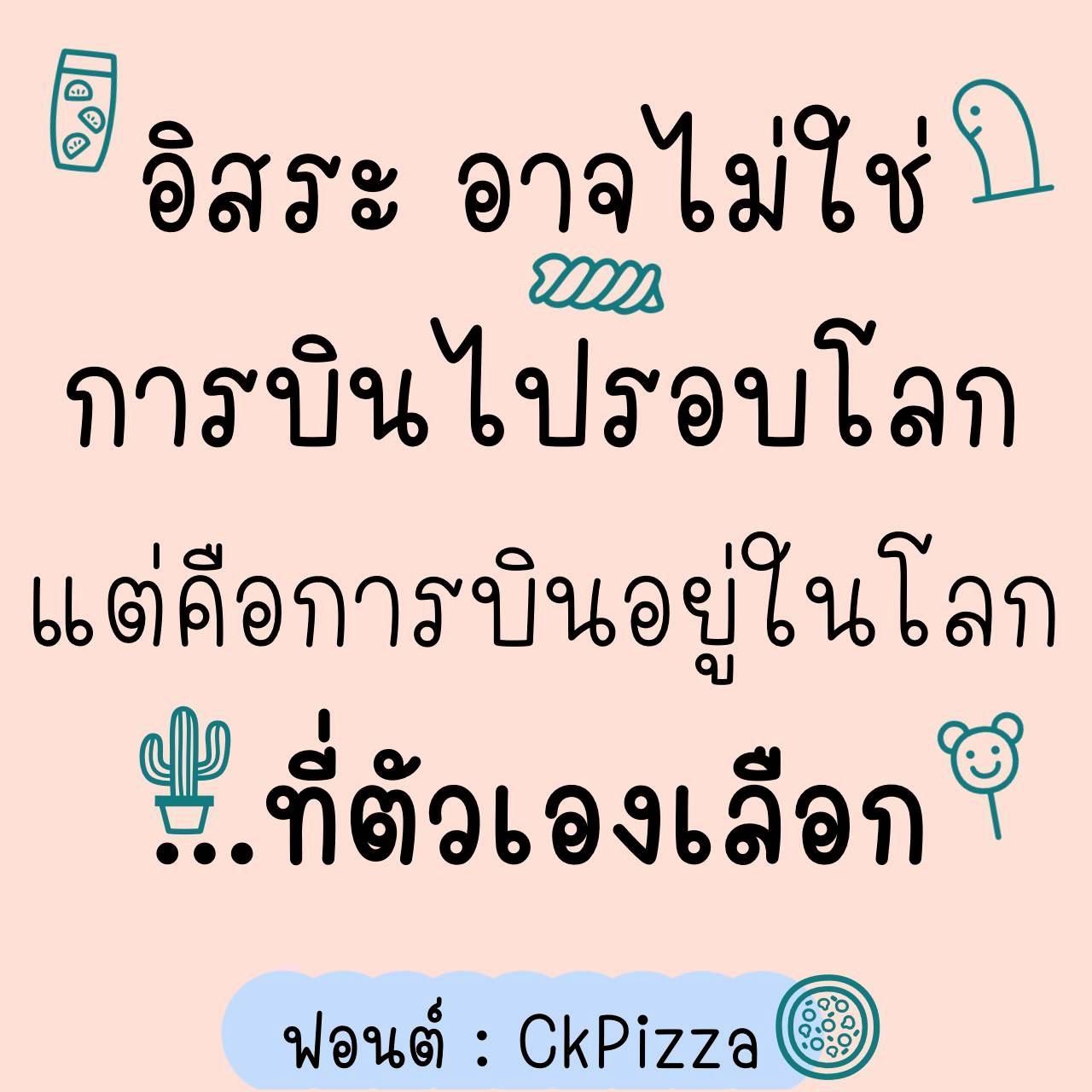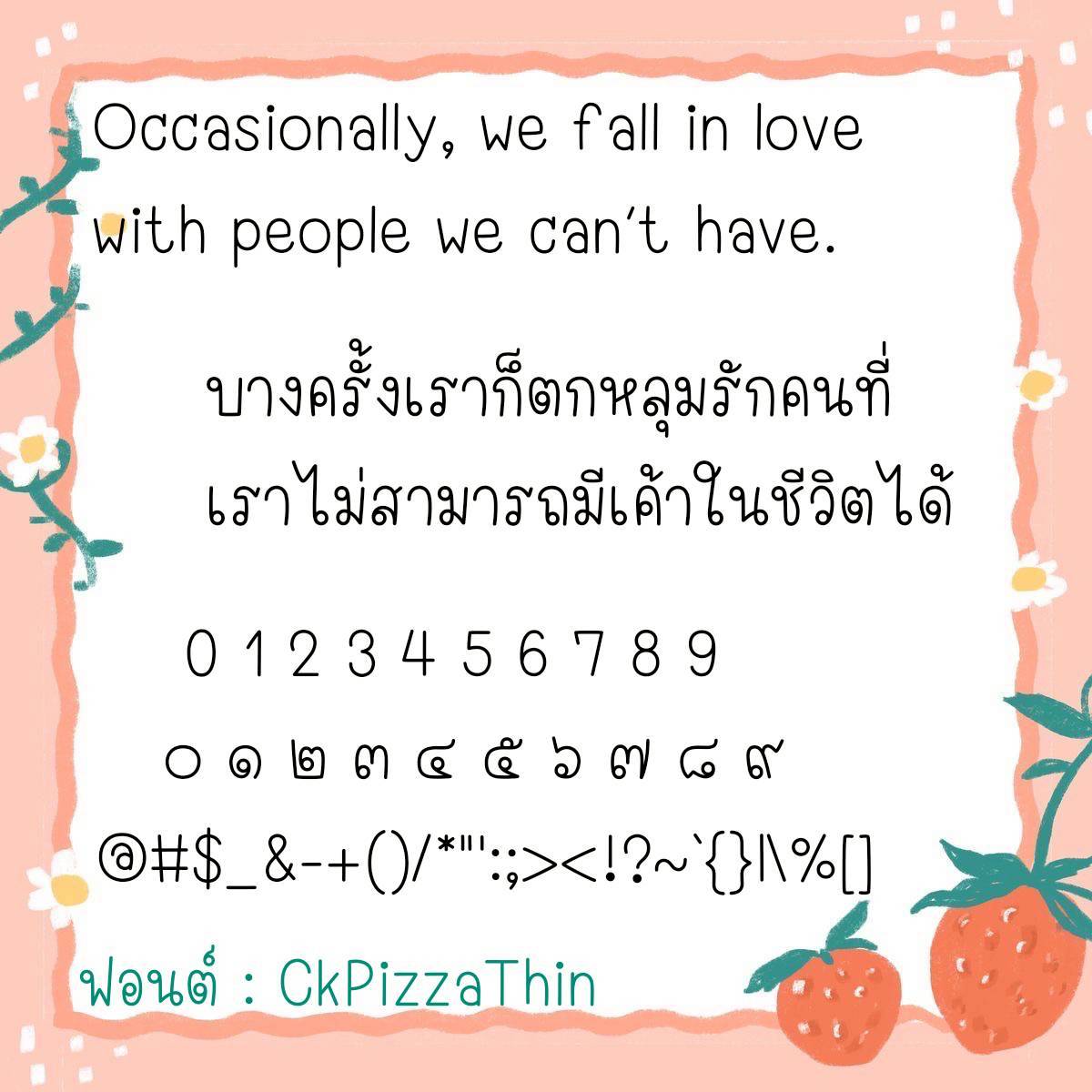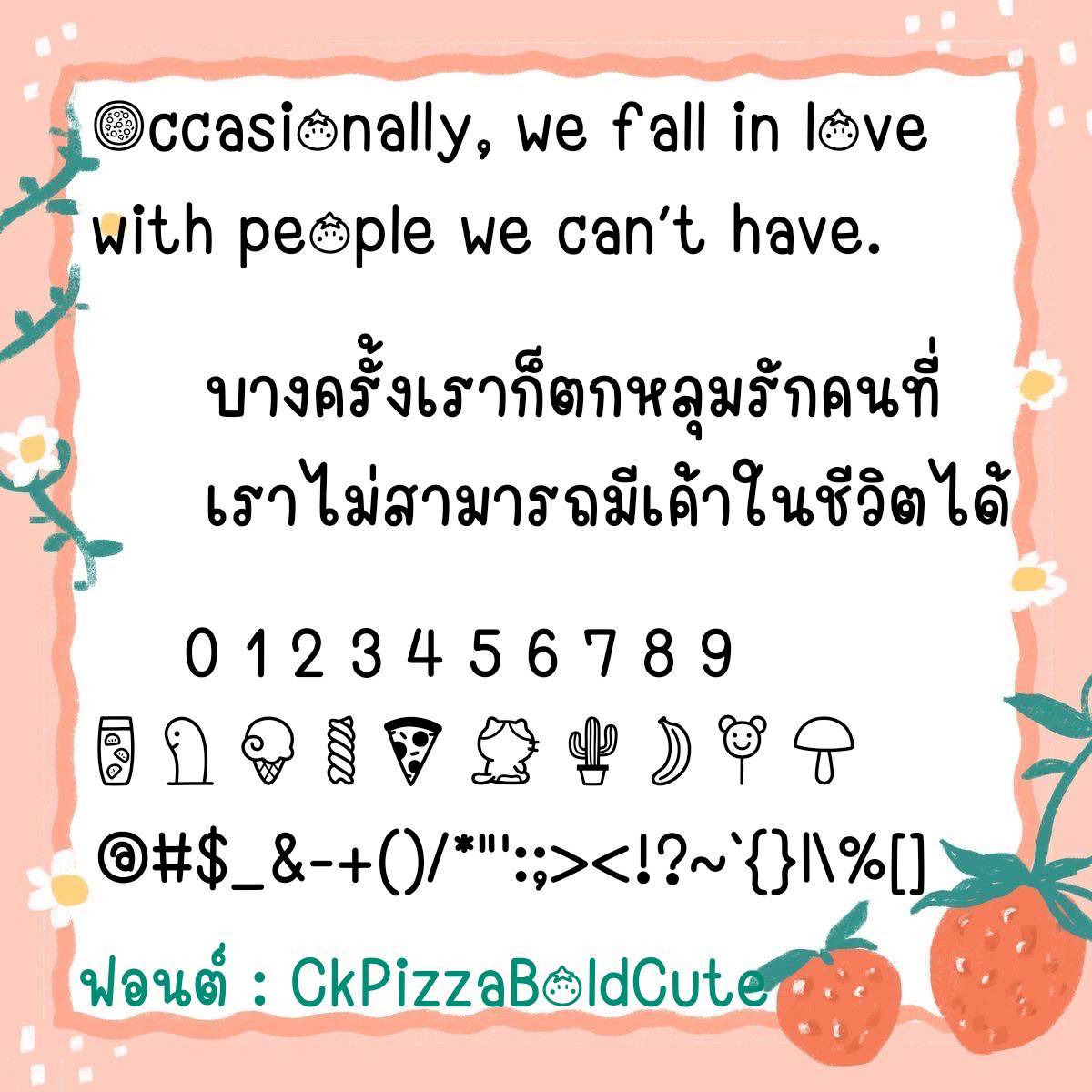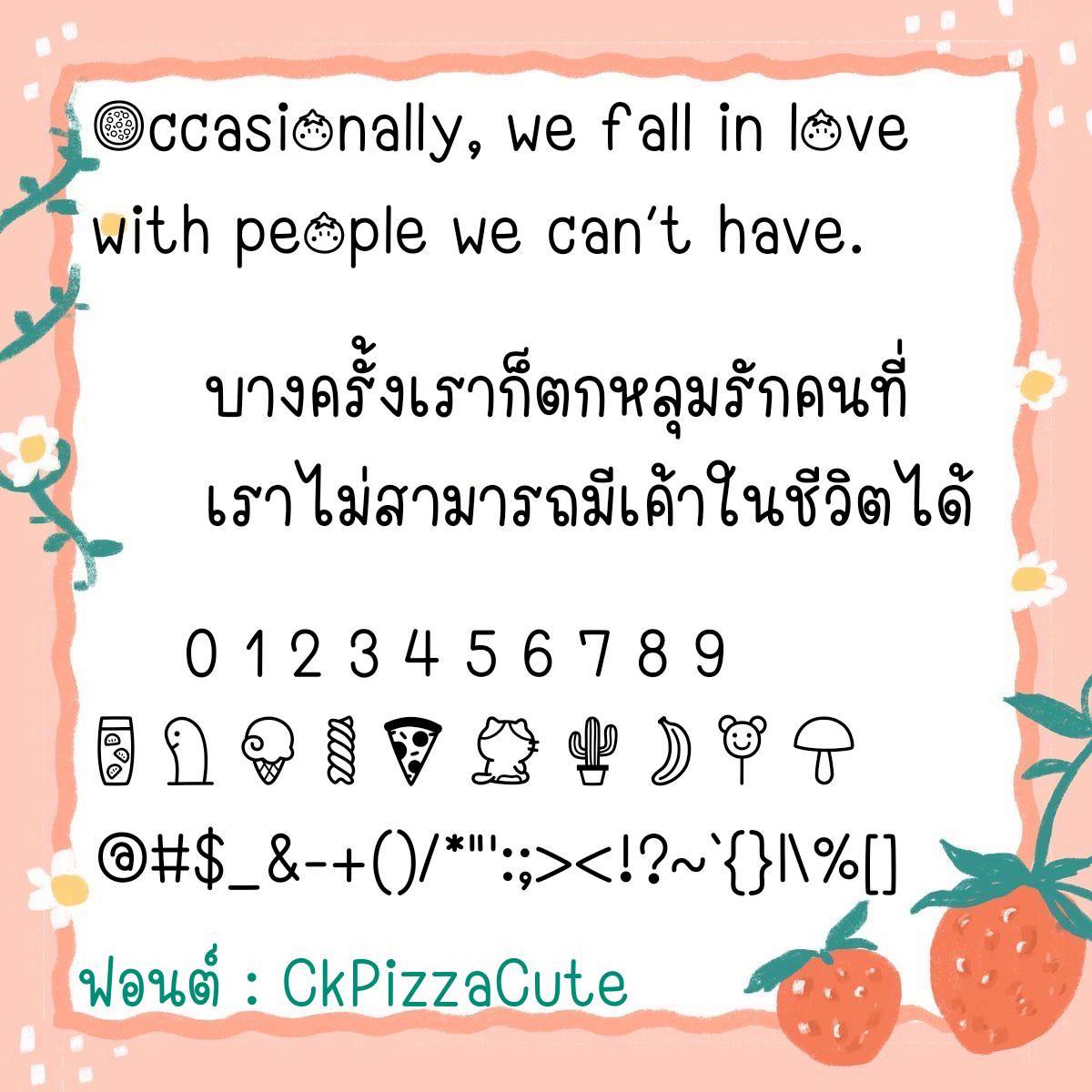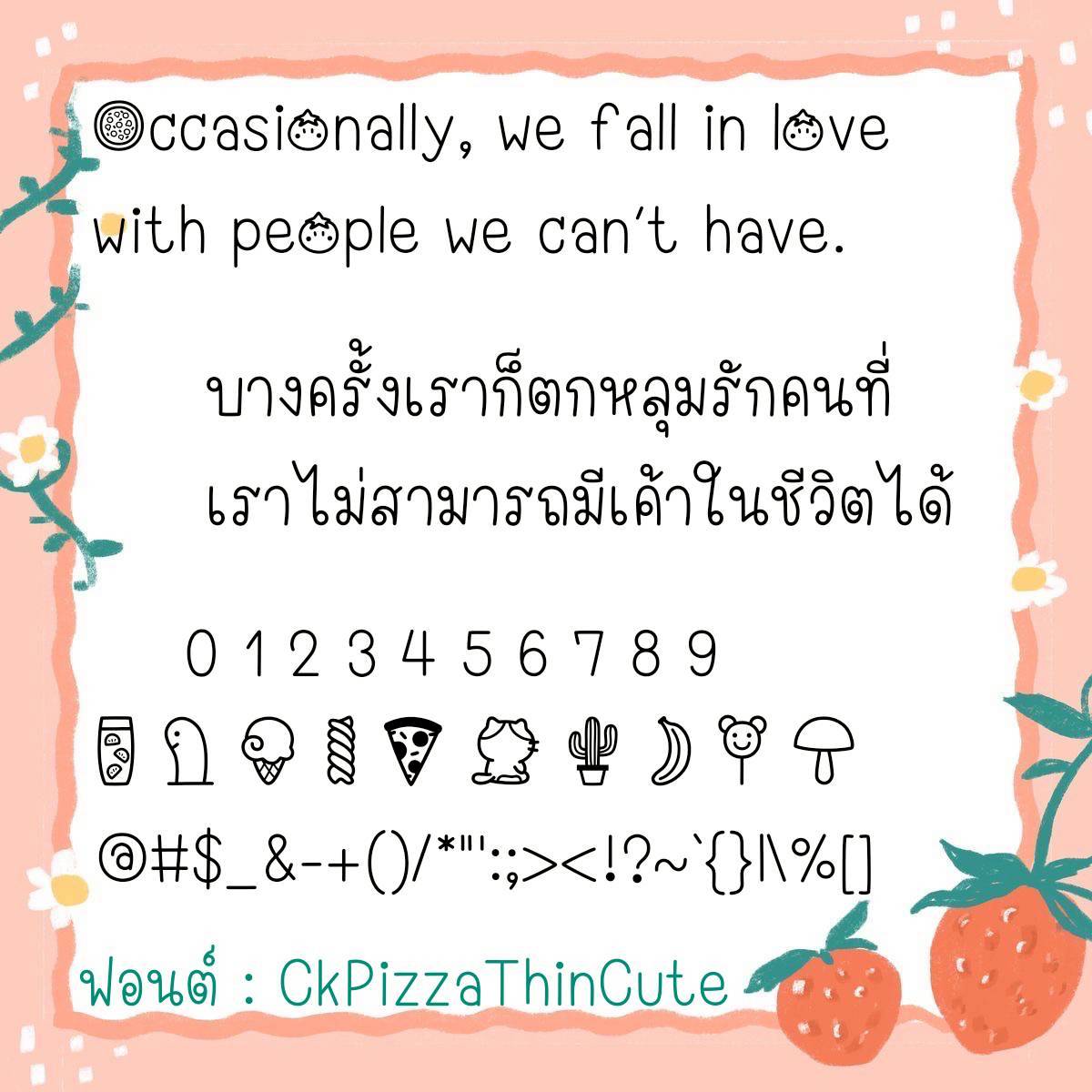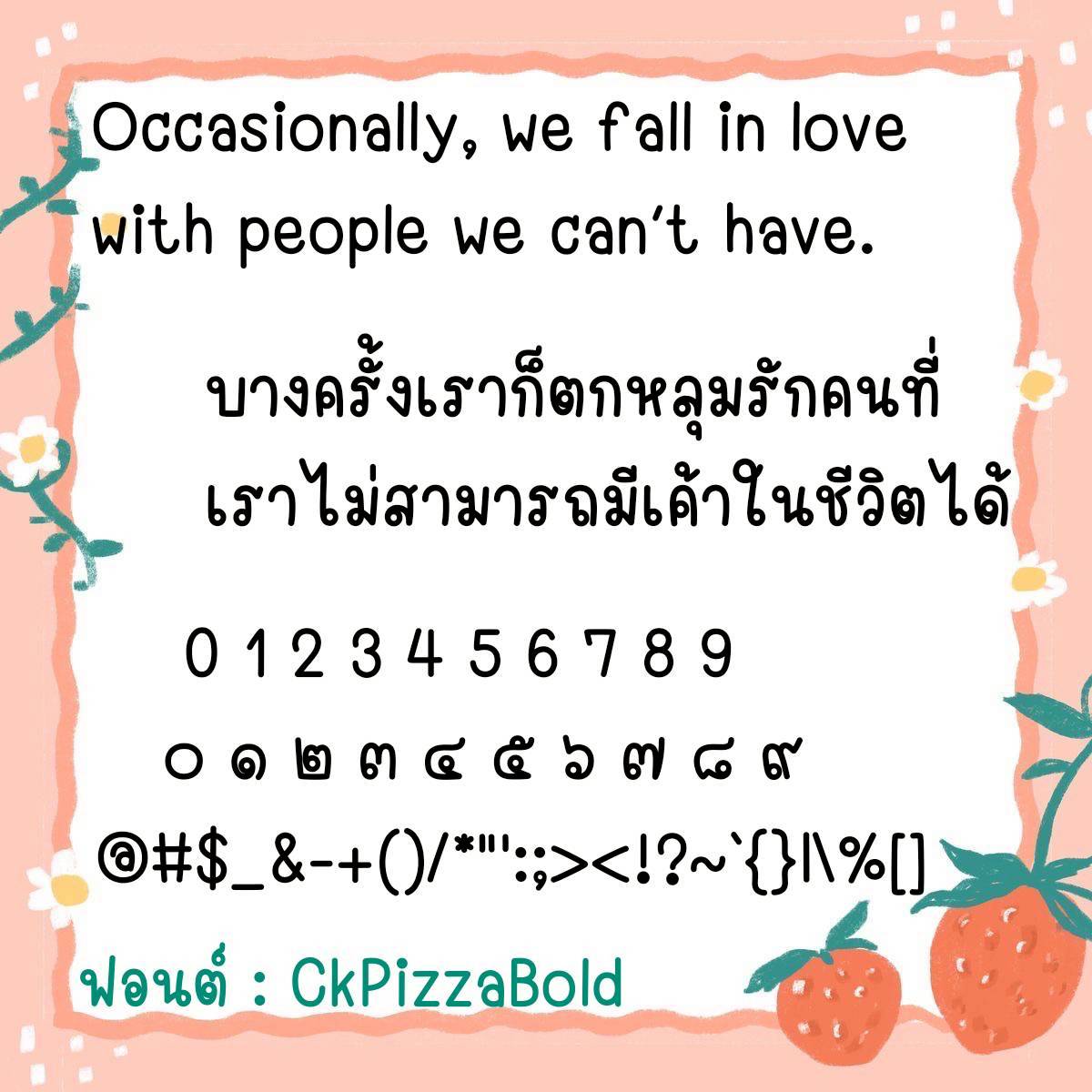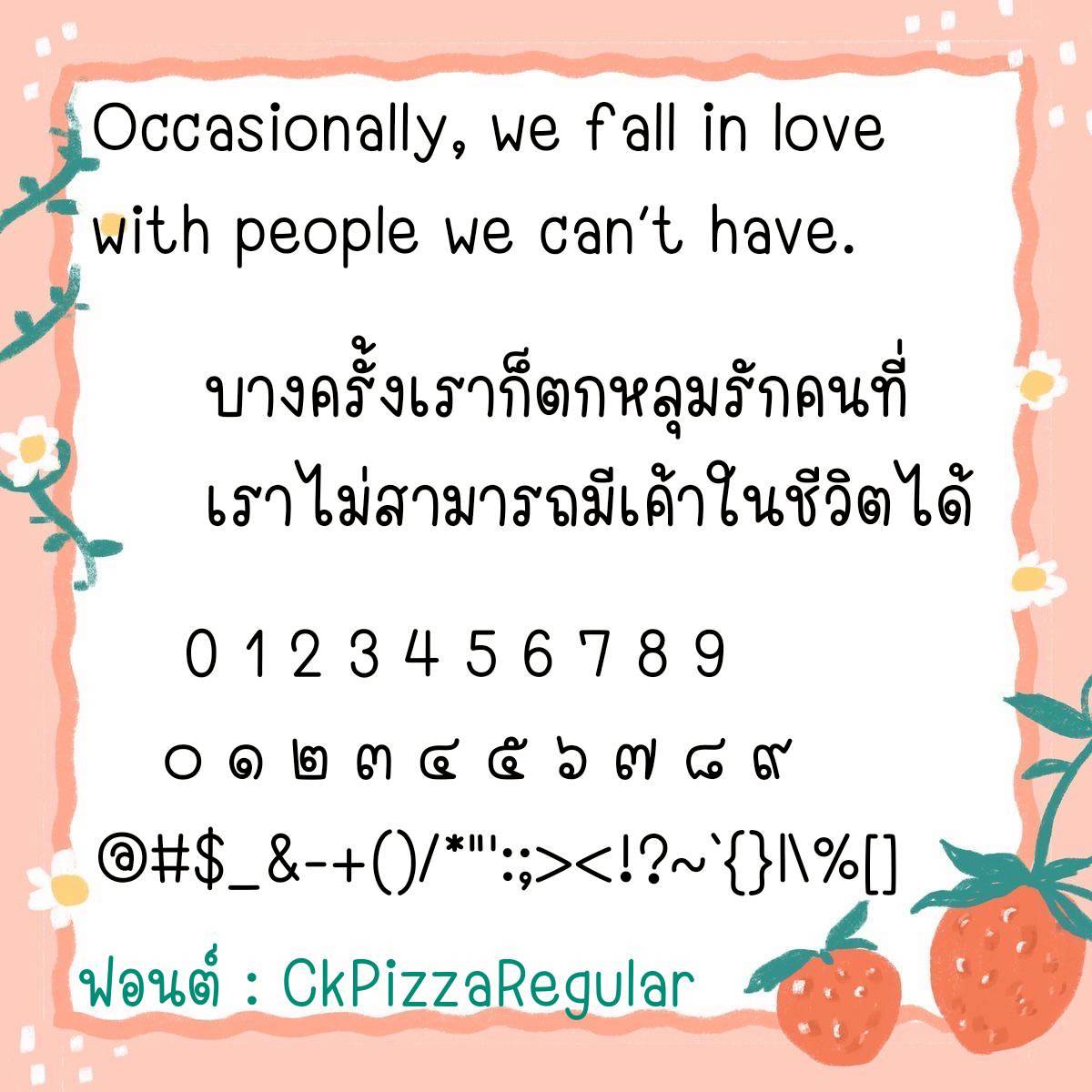
Font CkPizza
ชื่อสินค้า : Font CkPizza 💙
🔸 ฟอนต์ลายมือแนวน่ารักแบบวัยรุ่น ขนาดตัวพอดีๆ ใช้งานได้หลากหลาย เน้นให้อ่านง่าย และยังมีไฟล์อิโมจิน่ารักๆ ที่ใช้แทนเลขไทยให้ด้วยค่ะ 🥰💙
🔹 A cute, teenage-style handwriting font with a perfect size that can be used in many ways. It emphasizes readability and also has a cute emoji file that can be used in place of Thai numerals. 🥰💙